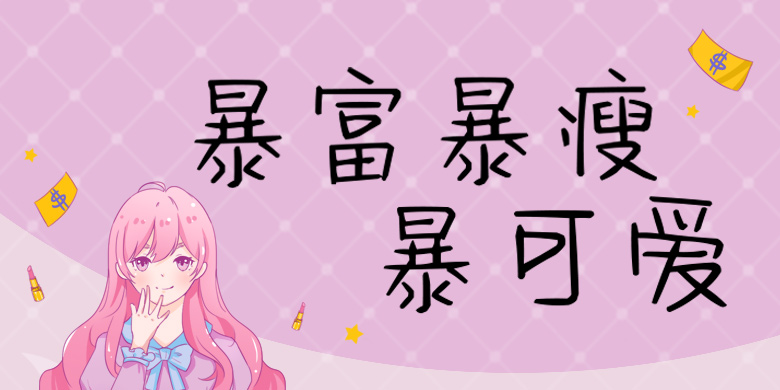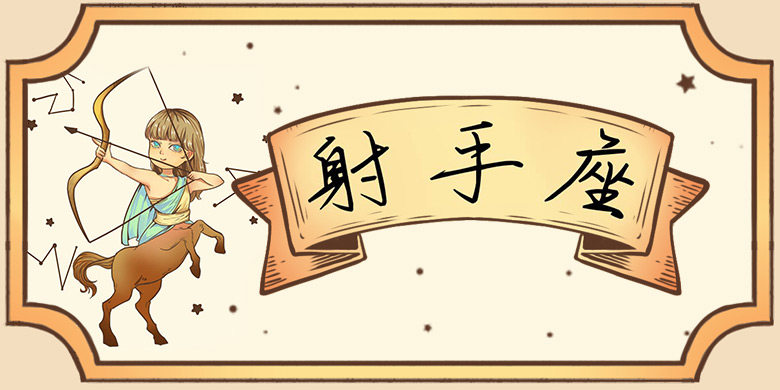
方正手迹-暴富暴瘦暴可爱字体说明方正手迹-暴富暴瘦暴可爱字体英文名称:FZSJ-BAOFBSBKA.TTF方正手迹-暴富暴瘦暴可爱品牌:方正手迹 设计师: 余丹发行时间:2019字库编码: 简繁扩展(GBK)分类: 创意书写字体属性: 心动字字体介绍将行书的连笔同可爱的结构相糅合,一笔一划的书写中,显得稚嫩可爱。适用于少年儿童类的书刊、品牌广告和产品包装设计,以及社交网络的个性化用字。字体下载地址官网下载 发布日期 2020年7月20日 发布于 方正字体 标签 pop, 字体, 心动字, 方正, 繁, 行书 上篇文章: 方正手迹-高冷面瘫-摩羯座 下篇文章: 方正手迹-腹黑高冷-天蝎座 发表回复 取消回复要发表评论,您必须先登录。